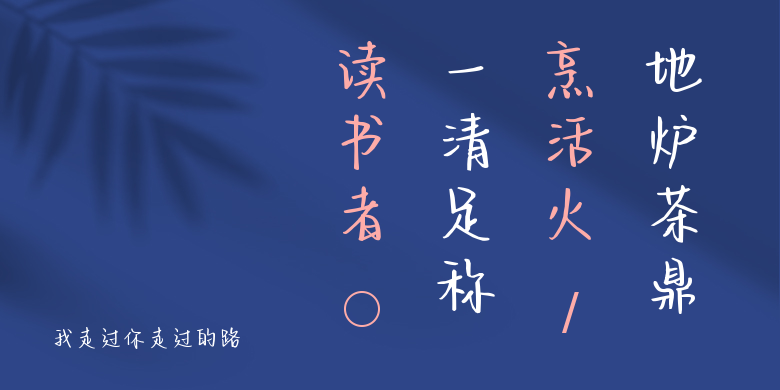
我走过你走过的路
我走过你走过的路,这款字体结构工整、笔画清晰,兼顾美观与易读性,适用于标题、正文、海报、包装、LOGO 等多种场景。字形优雅稳定,风格百搭耐看,适配日常排版与创意设计,让文字呈现更舒适、更具质感。我走过你走过的路一笔一画,皆是细节,以均衡的比例、流畅的线条打造舒适视觉体验,字形端正大气,风格简约现代。无论是商业设计、品牌宣传还是日常排版,都能轻松驾驭,让文字更有格调与力量。我走过你走过的路字体下载。